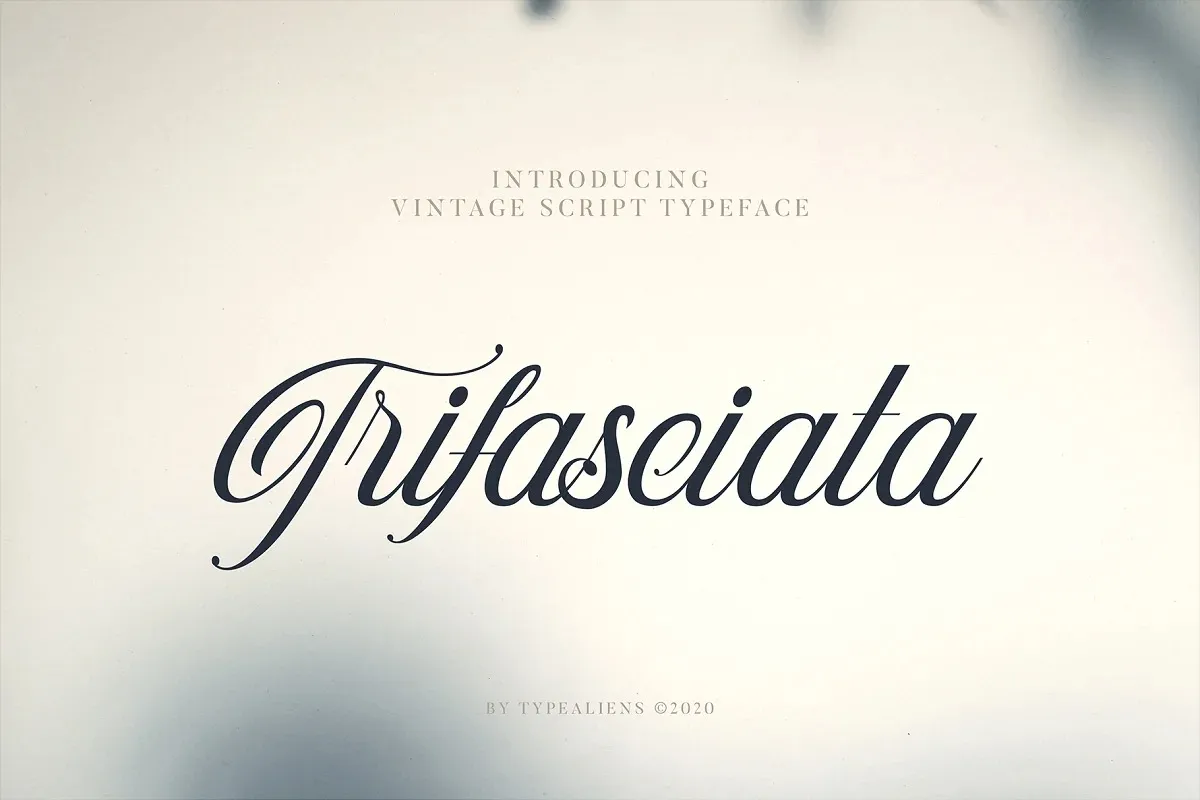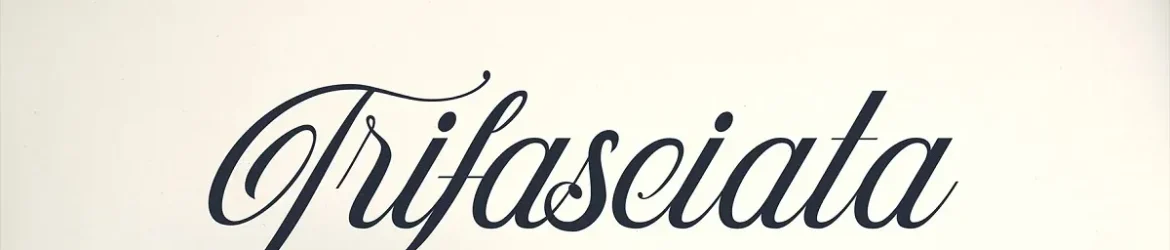
A Trifasciata Font é uma tipografia script que foi cuidadosamente criada pelo ilhamtaro para oferecer aos designers alternativas estilizadas e espirais incríveis. Esse tipo de letra, feito à mão, contém diversas opções estilizadas que permitem ao designer criar suas próprias soluções únicas. Como uma fonte script, a Trifasciata é perfeita para aplicação em textos legíveis e elegantes, ou mesmo para gráficos de design de marca com um toque único. Essa fonte é ótima para quem quer adicionar personalidade e estilo às suas criações digitais. A Trifasciata Font oferece uma maneira fácil e poderosa de tornar cada projeto um pouco mais pessoal, seja em cartazes, sites ou documentos pessoais.